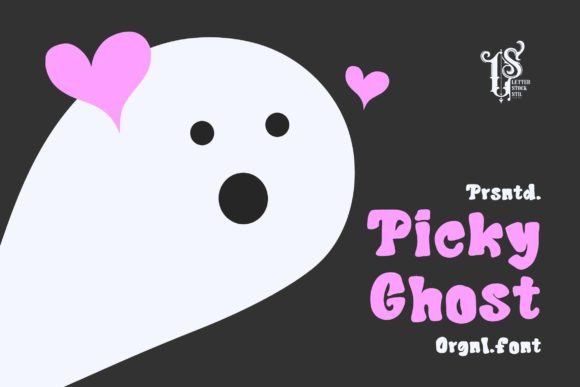
Picky Ghost
適切なデザイン要素を見つけるのは難しい場合がありますが、Picky Ghostは作品を即座に引き立てる優れたコレクションを提供します。
POD(オンデマンド印刷)製品、結婚式の招待状、またはソーシャルメディアのグラフィックを作成している場合でも、Picky Ghostは理想的です。